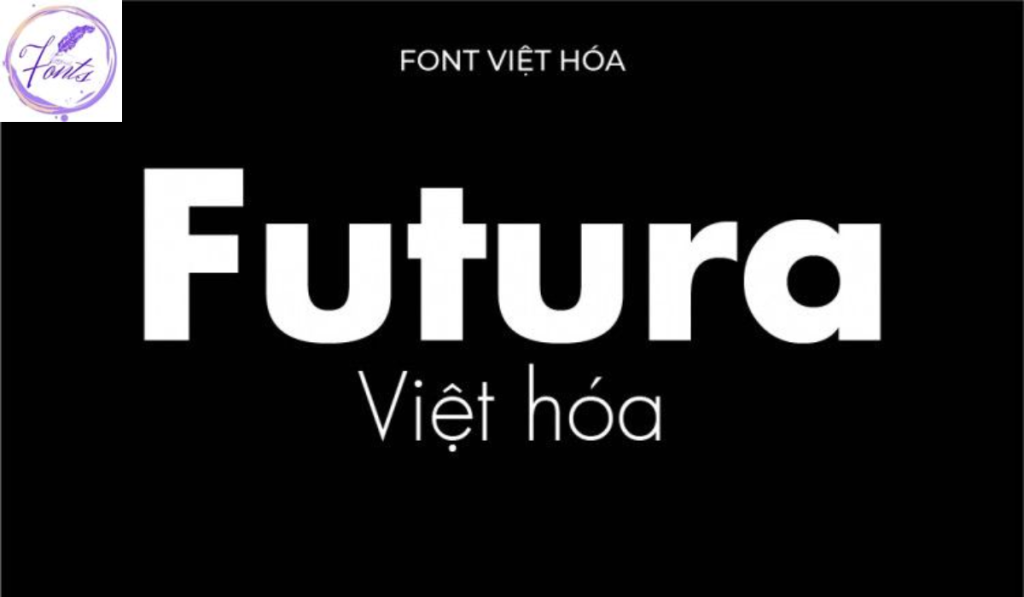
Font Futura Việt hóa
Tác giả: Paul Renner
Ngày phát hành: 1927
Bộ Font: Futura
Phân loại: Cá tính, hiện đại
Kiểu chữ: Không chân
Độ dày: Light, Book, Medium, Bold, Extra Bold, Black, Condensed
Font Futura Việt hóa – một trong những font chữ đẹp và được ưa chuộng nhất hiện nay! Font chữ Futura do nhà thiết kế Paul Renner công bố năm 1927, mang phong cách hiện đại và sang trọng. Trong bài viết này, chúng ta sẽ cùng tìm hiểu về nguồn gốc, đặc điểm nổi bật của font Futura, cũng như cách tải và cài đặt font Futura Việt hóa một cách nhanh chóng và dễ dàng nhất.